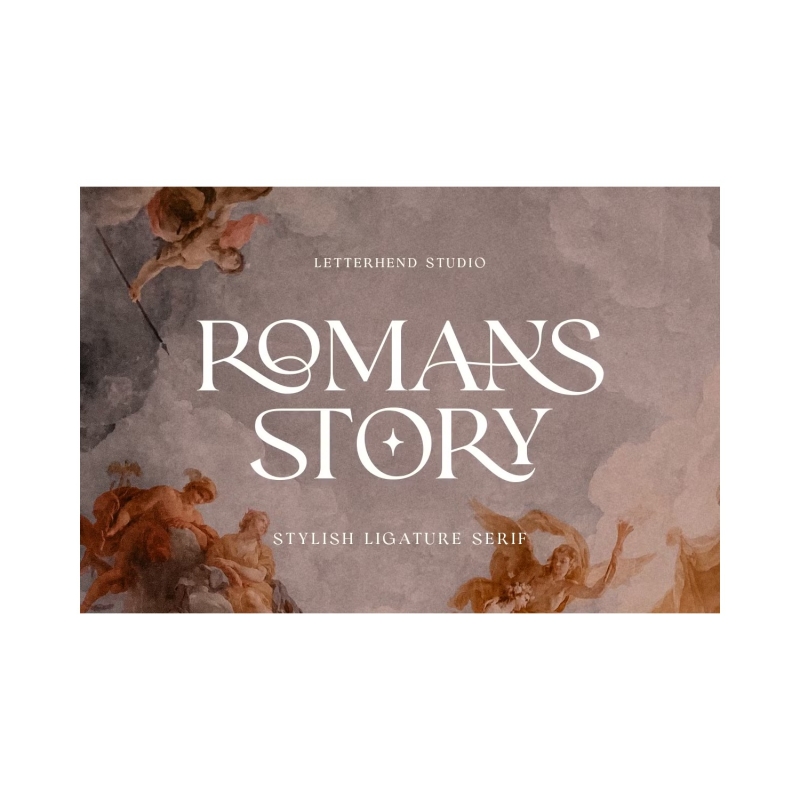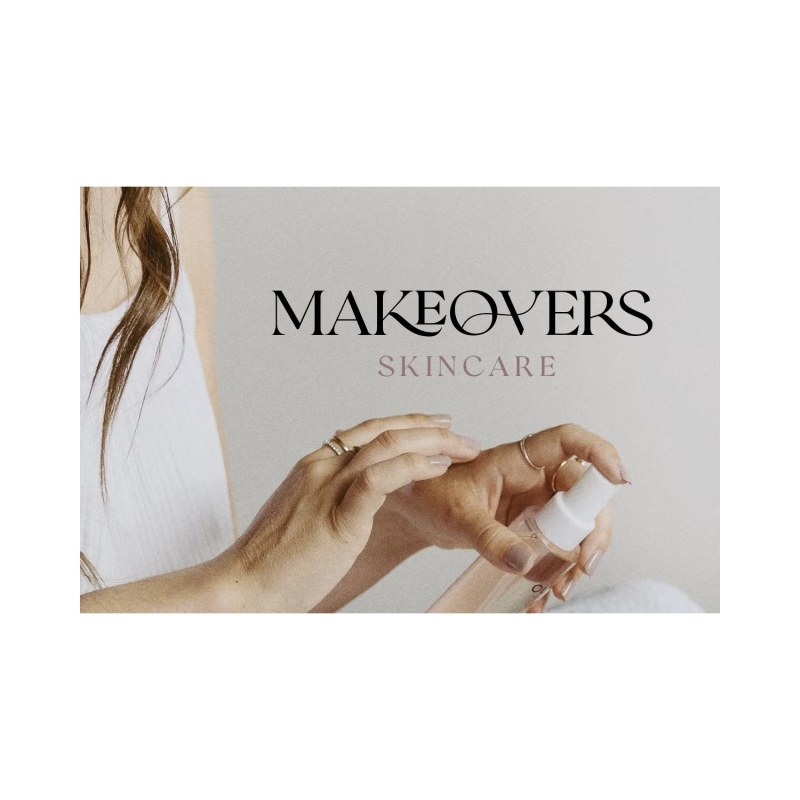
قصة الرومان - خط الرباط Serif
• ملامح: الحروف المركبة
• ملامح: الأرقام وعلامات الترقيم
• ملامح: متعدد اللغات
قصة الرومان هي رباط متطور منا. تم صنع هذا الخط بعناية للتأكد من جودته الممتازة وشعوره بالرفاهية. تجعل الأحرف المركبة هذا الخط فريدا ويبرز بدلا من الخط الرقيق العادي. مناسب جدا للشعار والعنوان الرئيسي والشعارات والأشكال الرسمية المختلفة الأخرى مثل الدعوات والملصقات والشعارات والمجلات والكتب وبطاقات المعايدة / الزفاف والتعبئة والتغليف والأزياء والمكياج والقرطاسية والروايات والملصقات أو أي نوع من الأغراض الإعلانية.
ملامح:
• الأرقام وعلامات الترقيم
• متعدد اللغات
• الحروف المركبة
• المناوبين